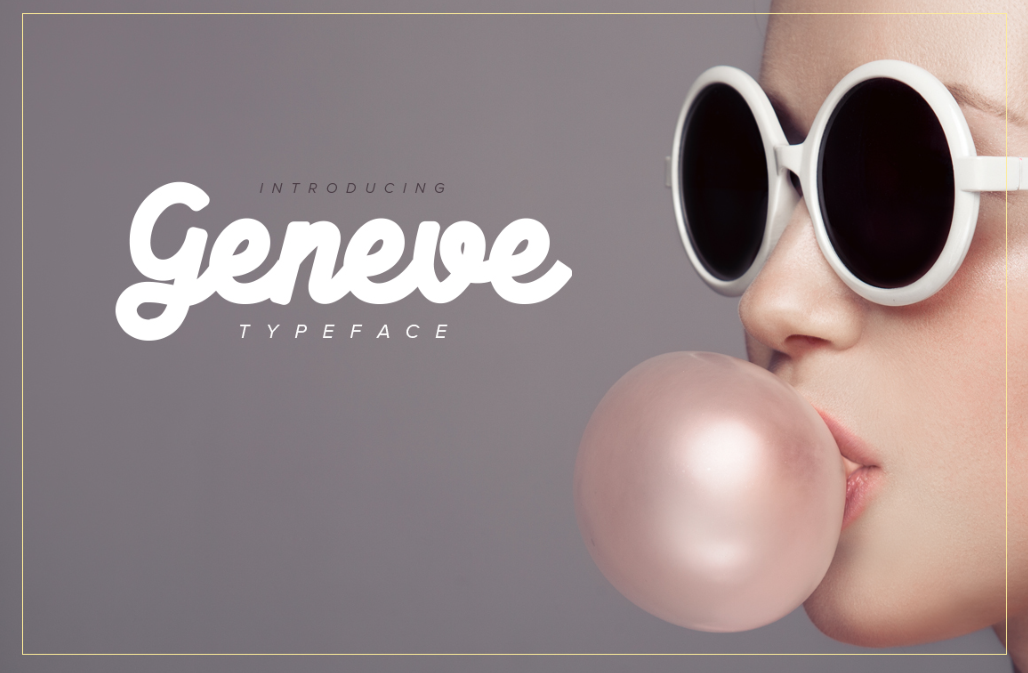
A Geneve Typeface é uma elegante fónt que combina força e simplicidade com leveza círula e amizade. Oferecida por 178-MC, esta fonte bold é perfeita para quem busca destaque em qualquer aplicação: seja em pacotes de produto, identidades visuais, designs web ou até mesmo decoração de interiores. Além disso, a Geneve oferece muitos alternativos e recursos do OpenType, que permitem personalizar ainda mais sua utilização. É uma escolha ideal para um texto estilizado que se sobressai em qualquer fundo, seja ele texturado ou apenas uma imagem. Sua simplicidade e confiabilidade combinam perfeitamente com a modernidade dos designs digitais atuais.